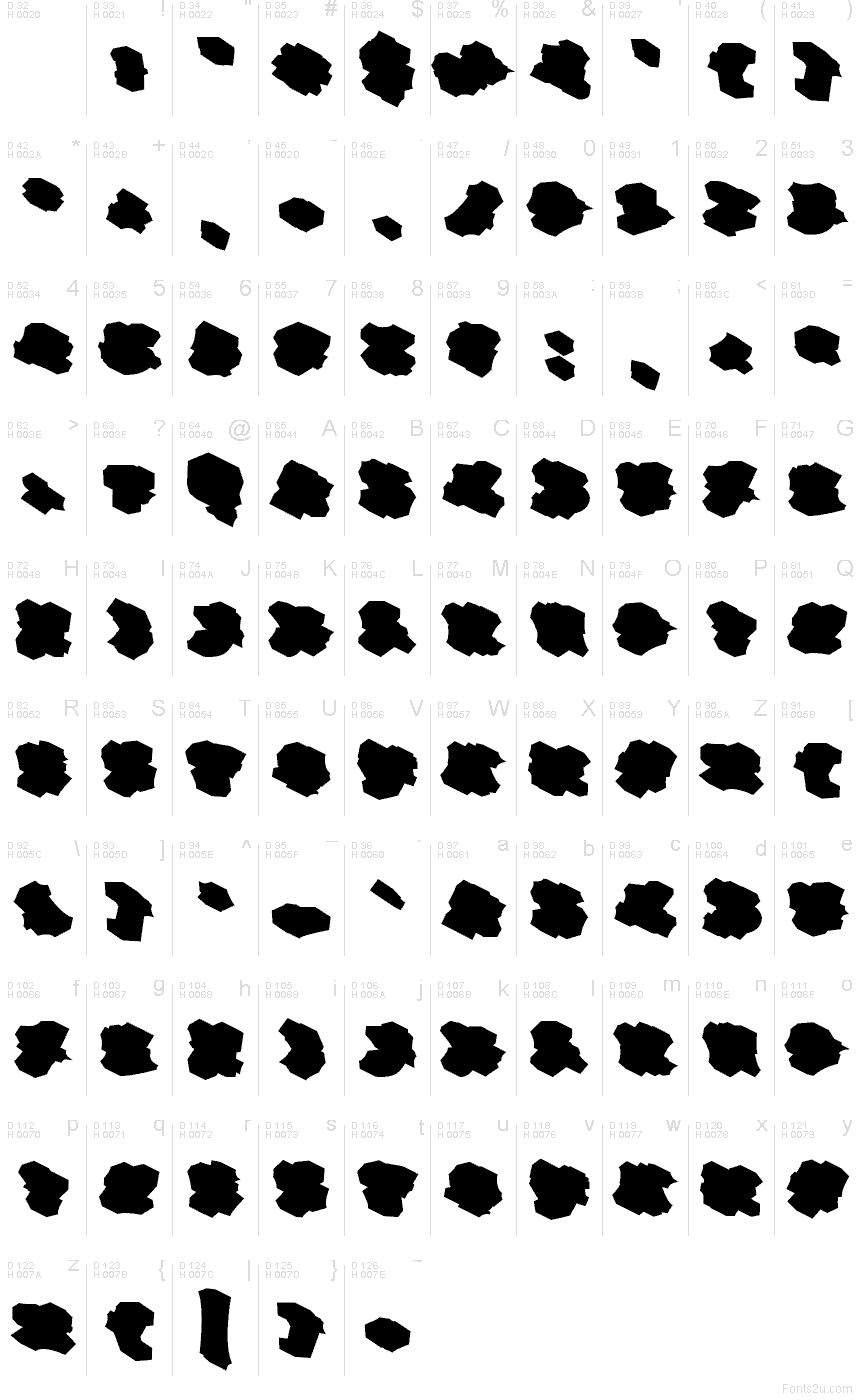
Nightclaw Vandal Extrude, realizzata da Muhammad Panji Ramdhani e Ferbiya Rahmat di Cikareotype, è un font graffiti gratuito. Colpisce come vernice fresca su mattoni: tratti spessi con bordi frastagliati e graffianti, e una profondità estrusa che rende ogni parola scolpita, solida e d'impatto. La spaziatura stretta mantiene il messaggio compatto, mentre la silhouette ruvida aggiunge quell'atmosfera street senza perdere definizione.
Usa Nightclaw Vandal Extrude su copertine di album, tag streetwear, poster da skate, miniature per gaming, volantini, intestazioni YouTube o loghi audaci per un'attitudine immediata. Impostalo in dimensioni grandi per far respirare i contorni frastagliati e abbina questo font gratuito con un sans serif condensato e pulito per date, crediti o prezzi.